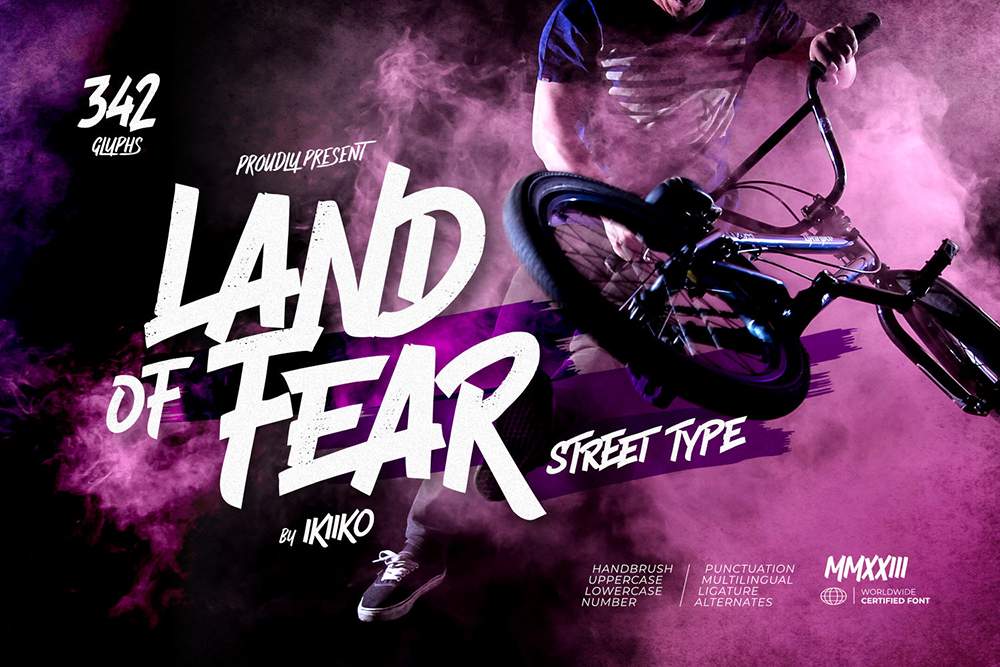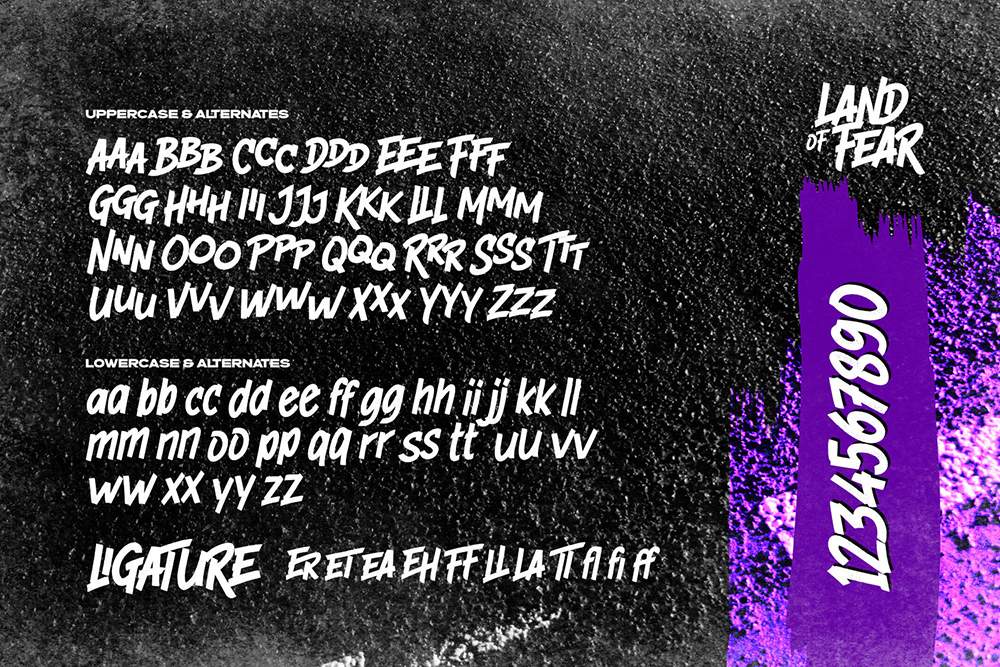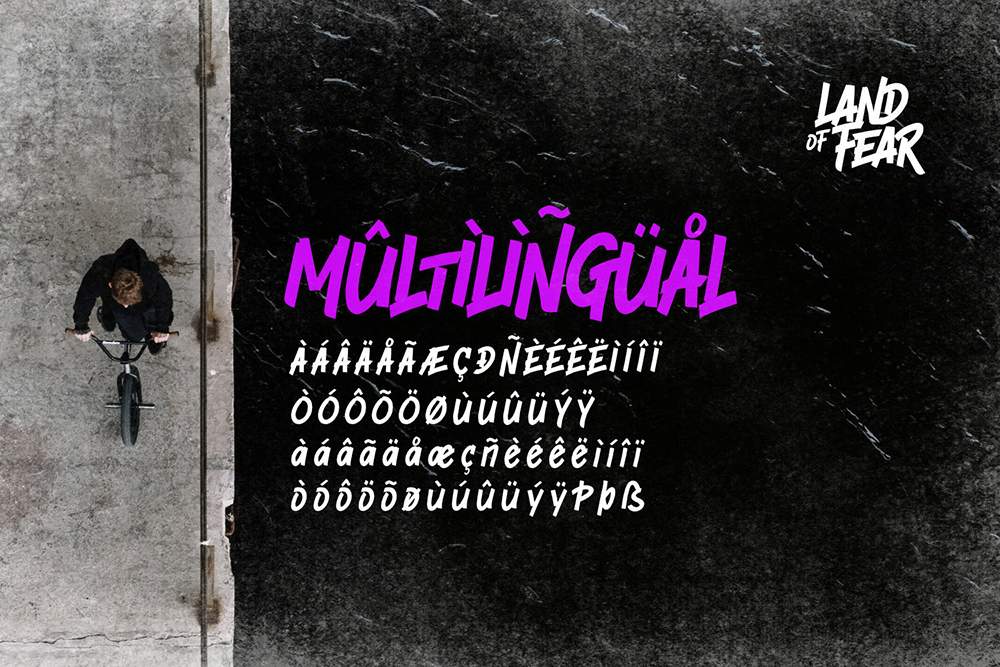
فونت پرمیوم و انگلیسی Land Of Fear Font یک فونت خيابانی به سبک شهری است که ظاهری خشن و تيز دارد و زمختی خيابانهای شهر را منتقل میکند. حروف دارای کاراکترهای پررنگ هستند که به سرعت با يک قلم موی قوی خراشيده میشوند. اين فونت دارای خطوط وحشی است و به حروف حس خودانگيختگی و سرزندگی میدهد و برای مطالب ورزشی، حال و هوای خيابانی، طرحبندي مجله، پوستر، برند مد، سبک شهری، نقل قولها يا به سادگی به عنوان يک پوشش متنی شيک برای هر تصوير پسزمينهای عالی است.
مزایای استفاده از فونت لاتین Land Of Fear چیست؟